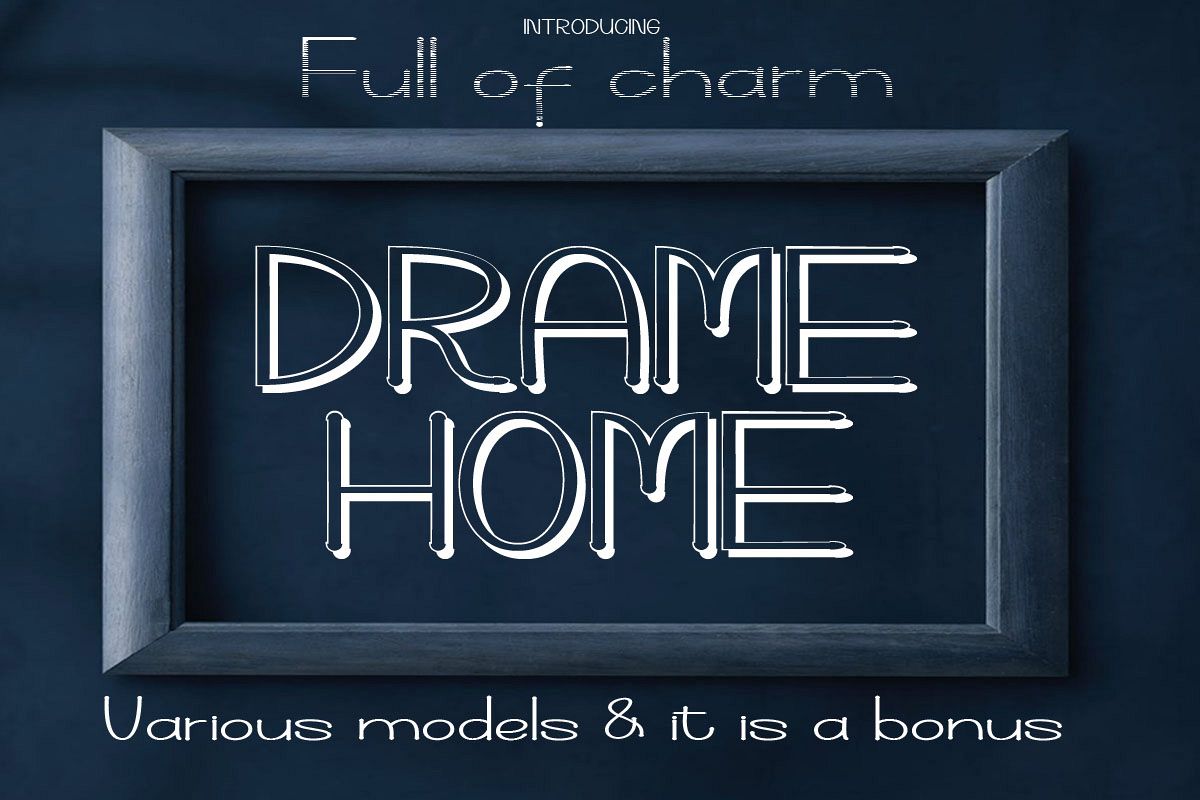
Drame adalah font yang sempurna untuk semua desain menyenangkan Anda. File font utama dilengkapi dengan karakter reguler dan juga karakter beraksen untuk mendukung sebagian besar bahasa berbasis Latin. Plus,